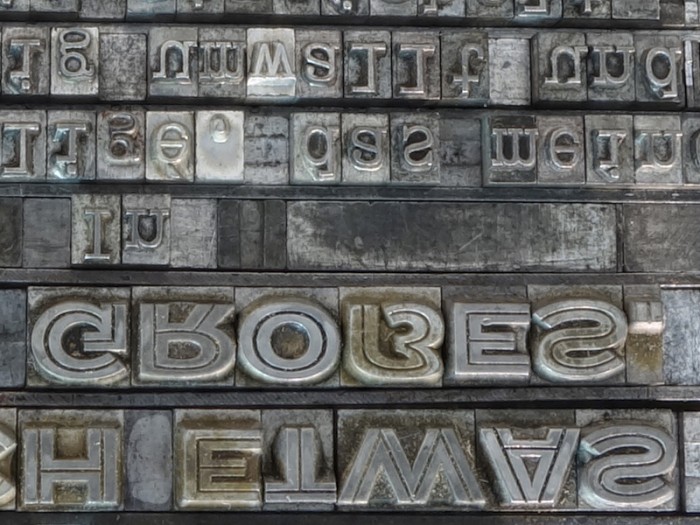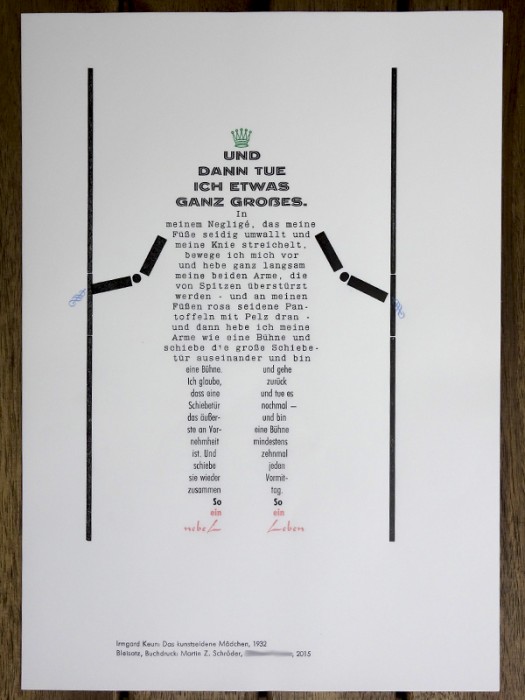
Jugendbildungsarbeit mit großem Eszett
Während eines dreiwöchigen Schülerpraktikums in meiner Werkstatt entwarf, setzte und druckte ein Fünfzehnjähriger mit meiner Hilfe ein Plakat im Format DIN A4. Die Schrift Koralle (Schriftgießerei: Schelter & Giesecke, Leipzig, Erstguß: 1915) habe ich nur wegen des großen Eszett ausgesucht. Gedruckt wurde das Plakat in vier Farben auf dem Heidelberger Tiegel.
Postkarte von meinem Jüngsten:
Allein die URL zeigt, dass die Arbeit um das ß noch lange nicht getan ist … :D
Hatten wir nicht irgendwo auch einen Artikel, der Eingabemöglichkeiten für das ẞ (wie die einfache Caps-Lock-Methode) erläutert? Hier …
… habe ich (bis auf eine Erwähnung der leider immer noch recht obskuren T2-Belegung) dazu jedenfalls nichts finden können.
Und wäre es vielleicht an der Zeit, den Wiki-Artikel mal zu überarbeiten bzw. in zwei Artikel zu trennen: einen mit relevanten Infos für ẞ-Anwender und einen mit Infos zur ẞ-Geschichte? Ich finde es ja hochspannend, was da von 2004 bis 2008 passiert ist. Aber für die Fragestellerin von heute Morgen, die wahrscheinlich nur an der aktuellen Situation interessiert ist, sieht das mglw. anders aus.